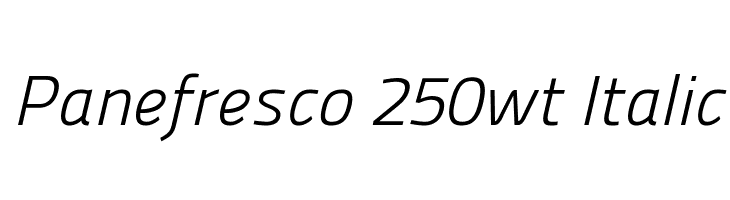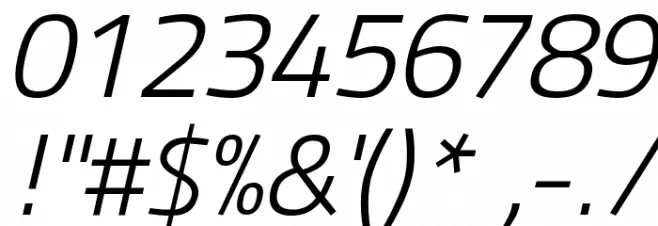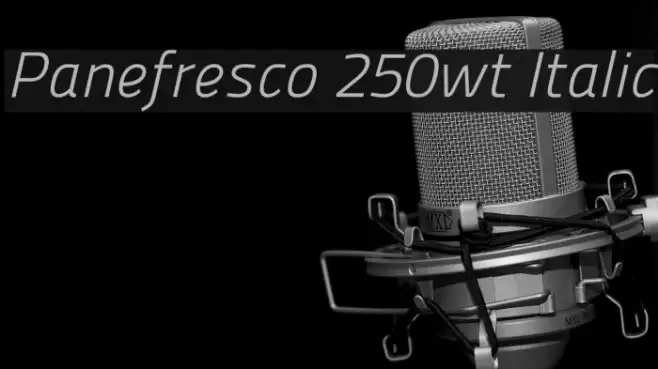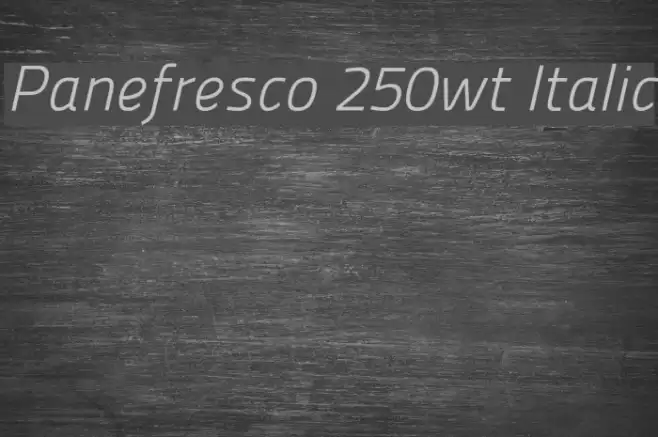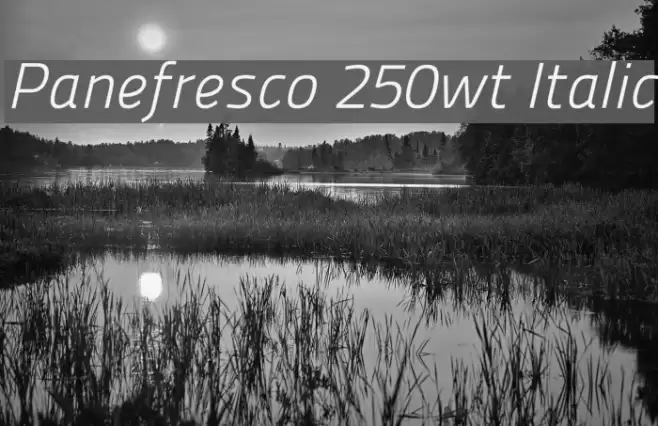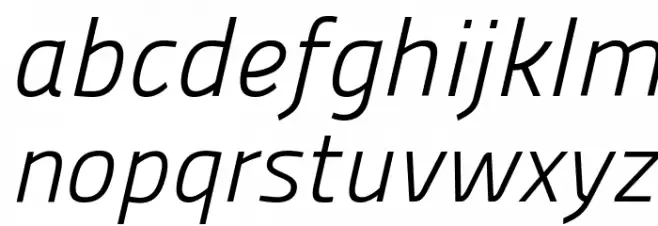
Panefresco 250wt Italic Font
✎ Sans Serif
| Anwendungsfall | Headlines, Body text, Logos |
| Vorgeschlagene Projekte | Ideal for branding, advertising, and editorial design projects where a modern and dynamic look is desired. |